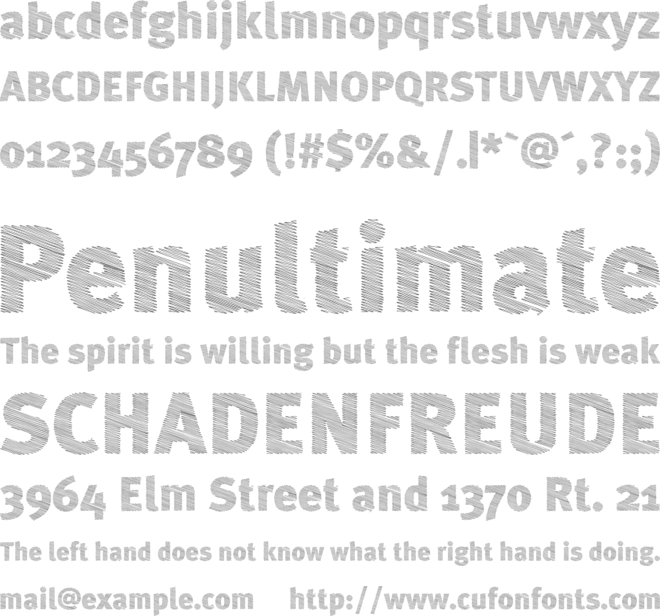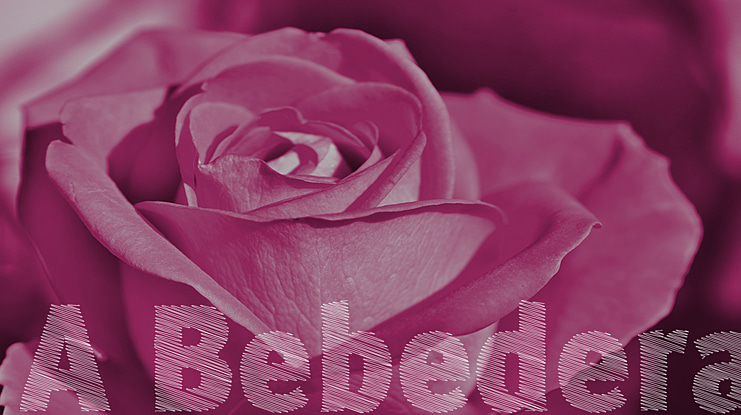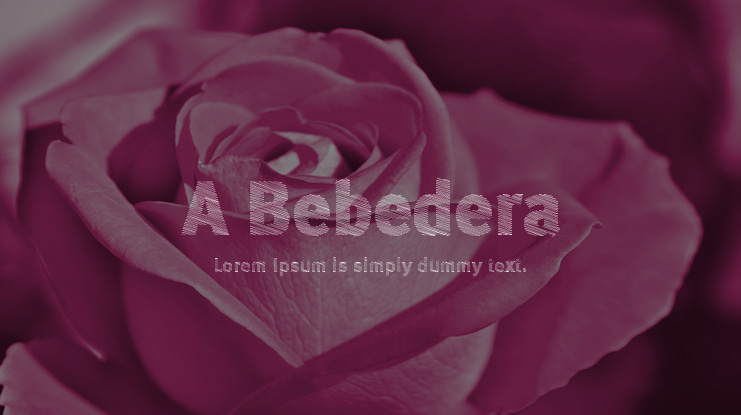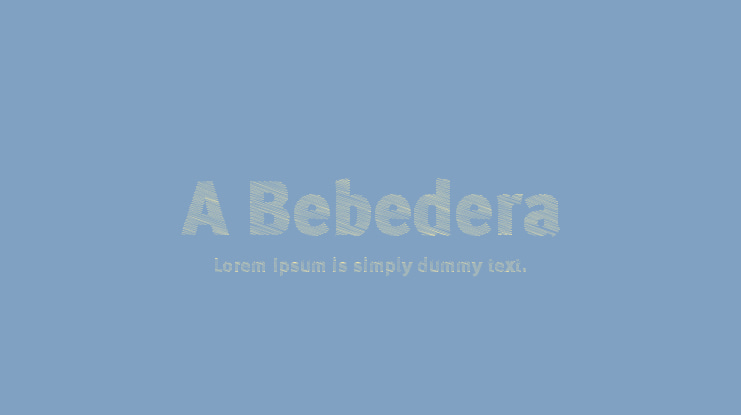
A Bebedera Font
A bebedera - esta frase portuguesa viene a significar la borrachera, le he puesto dicho nombre por la cantidad de curvas que tiene cada glifo... el vaiven del borracho, y el mareo que me he cogido haciéndola, también como homenaje a Brasil, donde viví y aprendí tanto.
Dispone de todos los caracteres del Latín.